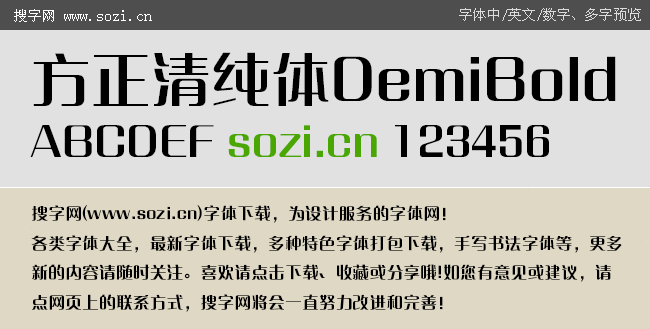
方正清純體DemiBold
搜字網(wǎng)提供一款方正清純體DemiBold中文藝術(shù)字體下載,方正清純體筆畫粗細(xì)對比明顯,橫細(xì)豎粗,筆形富于變化,整體給人清新、靈動(dòng)、優(yōu)美、圓潤之感,適合應(yīng)用于廣告設(shè)計(jì)、名片設(shè)計(jì)、包裝印刷、兒童產(chǎn)品設(shè)計(jì)等應(yīng)用。